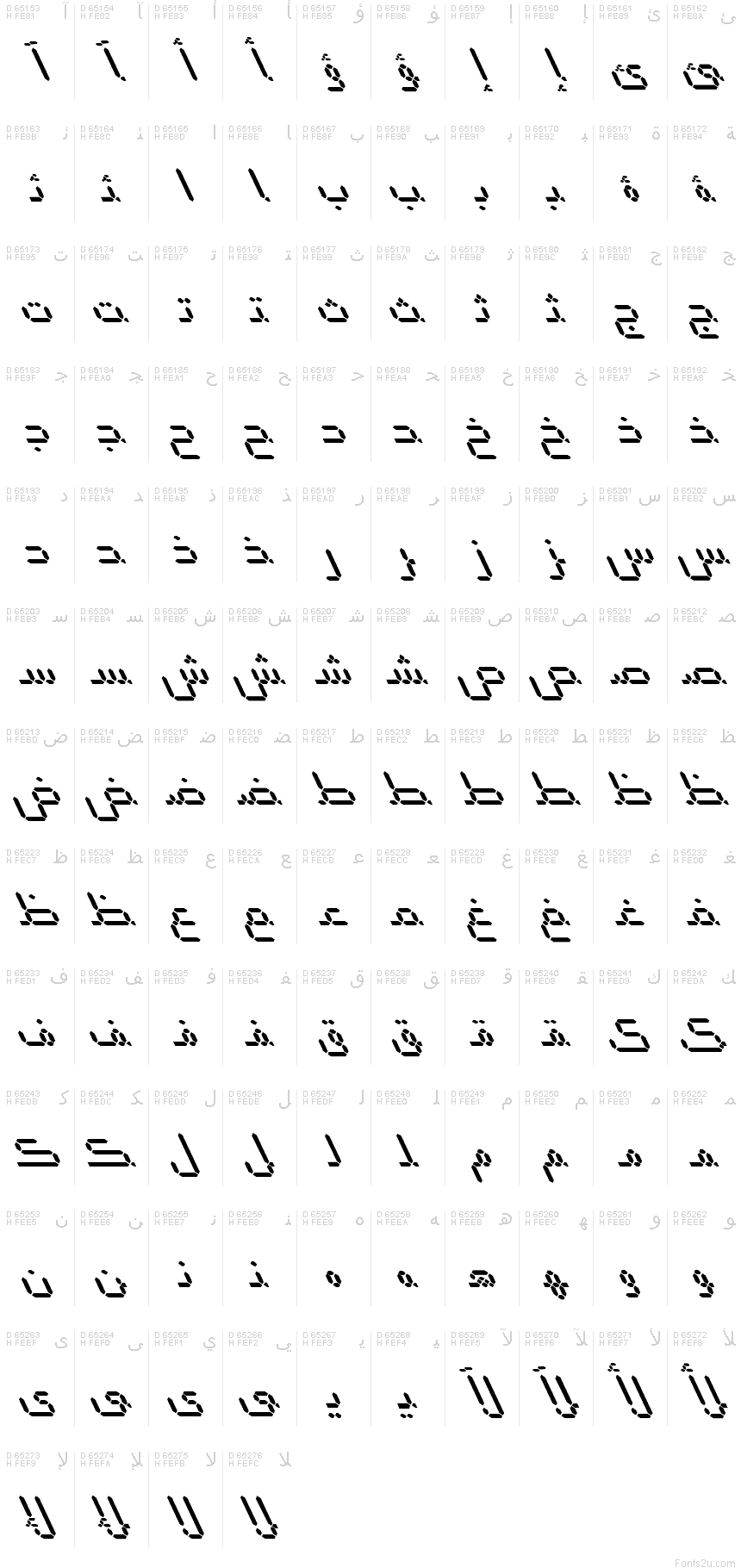
B Elm Italic od Borna Rayaneh je bezplatné arabské digitálne písmo určené na zobrazovanie. Tvarujú ho skosené, segmentované ťahy, ktoré skôr pripomínajú LED číslice než klasické písmená. Vďaka tejto opakovanej, akoby rozkúskovanej konštrukcii pôsobí dizajn kódovaným, strojovým rytmom. Písmo je preto ako stvorené na signály, počítadlá a grafiku na obrazovkách, nie na bežný text.
Podujatia, herné rozhrania, hlavičky aplikácií, hudobné obaly či technologický branding – všade tam využijete tento úsečný impulz. Bezplatné písmo najlepšie vynikne vtedy, keď potrebujete, aby nápisy pôsobili sviežo a synteticky. Pôsobí presvedčivo najmä v krátkych titulkoch, na úvodných kartách a v logách, kde segmentované tvary zostávajú ostré a čitateľné.